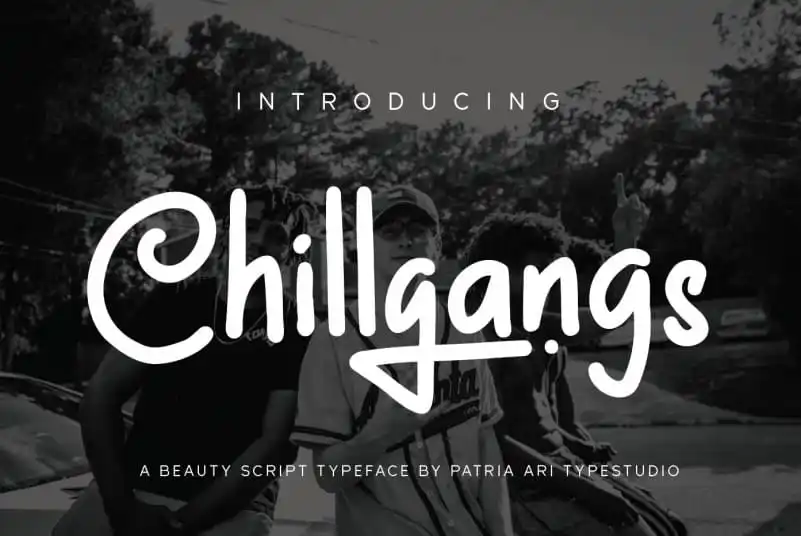
Chillgangs Script Font – Fonte Grátis
Chillgangs Script Font
A Chillgangs Script Font é uma tipografia exibida inspirada no graffiti, trazendo características únicas e desenhos alternativos que remetem ao movimento cultural do grafite. Esta tipografia monocilíndrica se destaca como um recurso ideal para diversos aplicativos, desde roupas até posts nas redes sociais, logotipos, embalagens de produtos e designs em geral. Suas formas alternativas e suas linhas arredondadas e fluidas são uma ótima escolha para designers buscando criar identidades visuais modernas e vibrantes. Composta com um tom alegre e despojado, esta fonte é perfeita para projetos que buscam transmitir uma atmosfera descontraída e autêntica, que são característicos do movimento graffiti. Suas linhas suaves se adaptam bem ao uso em diferentes ambientes de design, tornando-a um recurso valioso para qualquer projeto que deseja incorporar elementos gráficos atuais e icônicos.